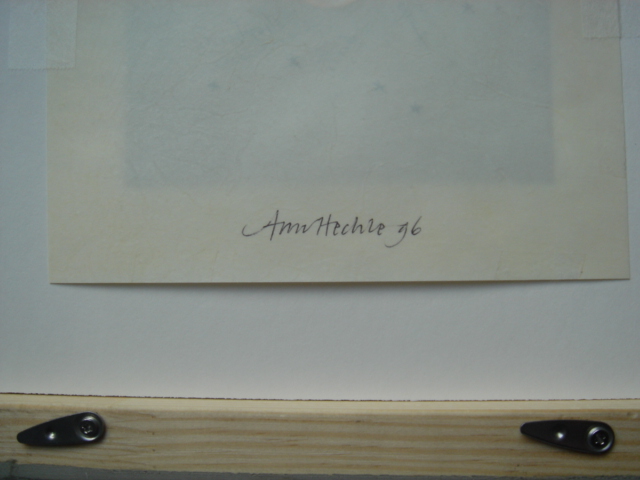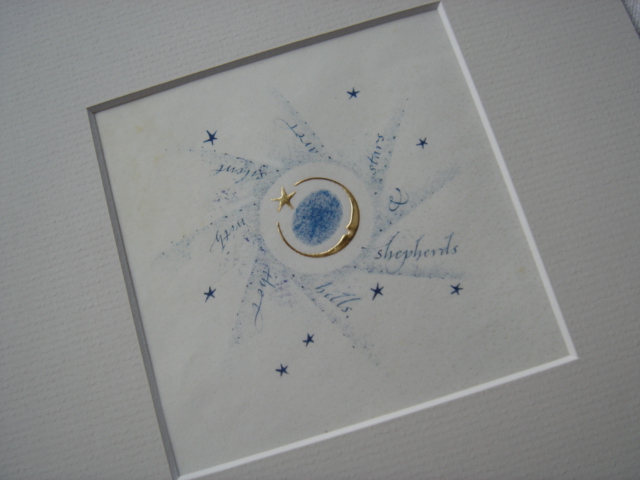
フレーム
銀の光のフレーム
ずっと机の前に飾ってあった作品をやっと額装に出し、出来上がってきました。
Ann Hechleの作品です。10センチ角ほどのとても小さな作品ですがなんといってもオリジナル。もう、美しいこと美しいこと!こんな額にしました。
作品の中心に金箔が使ってあるのですが、やっぱり月、星のイメージに合わせて銀色の入ったものにしました。フレーマーさんが「一応合わせますか?」と言って金色の額も見せてくれましたが、やっぱり銀色のほうが合いました。
いくつかシルバー系の額から決めることにしましたが、結局これになりました。
薄いブルーの上に銀色の塗料がかすれたように塗ってある木製の額です。
額のフチにすこ〜しだけ赤(サビているような色です)が入っているのが気に入りました。
マットは薄いグレーです。そっか、グレーか…自分で選ぶと無難に羊皮紙の色に合わせていたでしょうね。
作品は、以前mojitor-sさんも紹介していましたね〜、いつでしたっけ…?
ずっと以前のカンファレンスで購入したのです。
Ann Hechleの作品が買えるなんて!こんなチャンスを逃すわけにはいかない、と迷わず購入しました。しかも、私にも買えるお値段だったのです。本当かな?と半信半疑でお金を払った覚えがあります。
このテキストでいくつかデザインが少しずつ違うものがシリーズで出ていたので、sさんと私のほかにも手に入れた人がいると思います。
サインは内側にあります、と但し書きが外側に書いてあったのですが、ずっとバックボードをはずさずにいたのです。今回初めて開けてみました。サイン、ありました!あ、やっぱり10年以上も前だった。
本当になんて美しい文字なんでしょう。ほそ〜い線もきれ〜い!
確かミッチェルのペン先を更に削って書いていらっしゃるのでしたっけ?
やっぱり毎日いい字を見ていたいものです。
自分の作品を見ていても自分が進歩するわけでもないので…だから、今はAnn Hechleのとmojitor-sさんの作品で目に栄養を与えているところでーす。